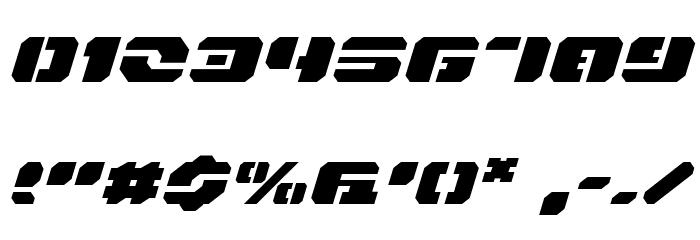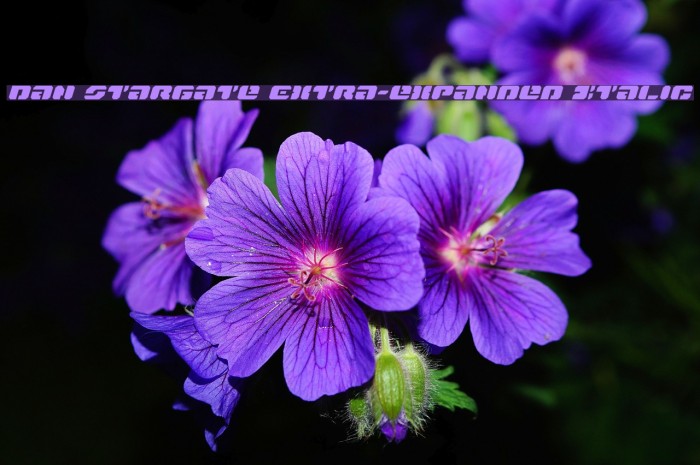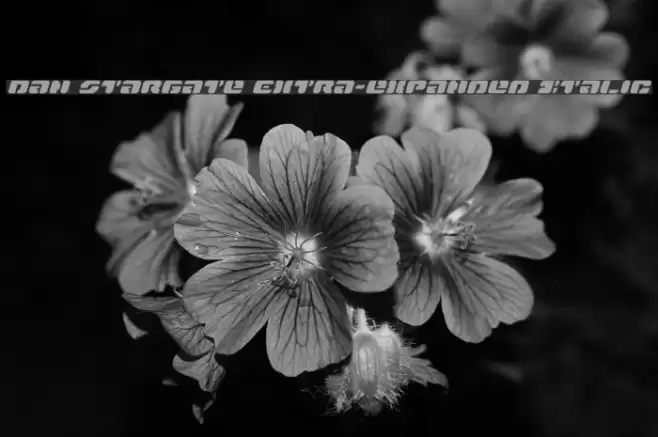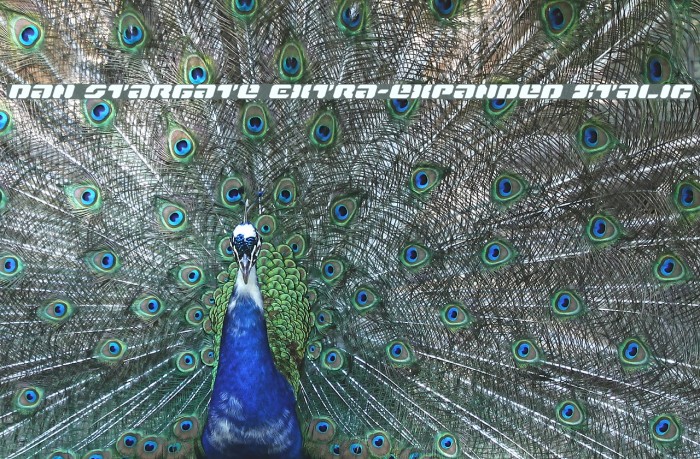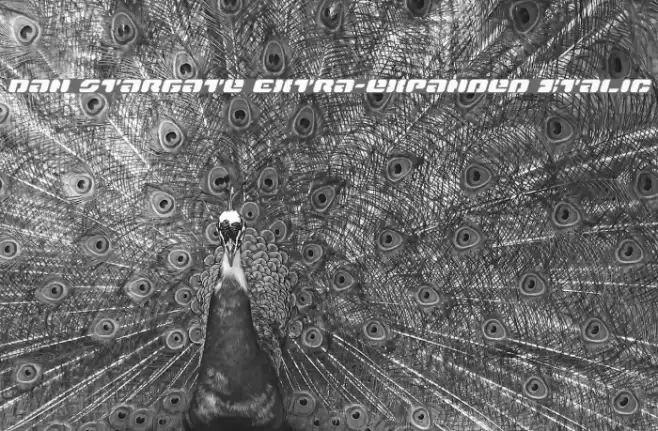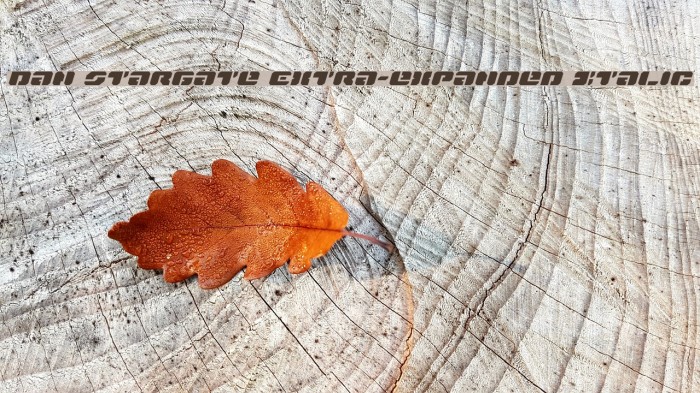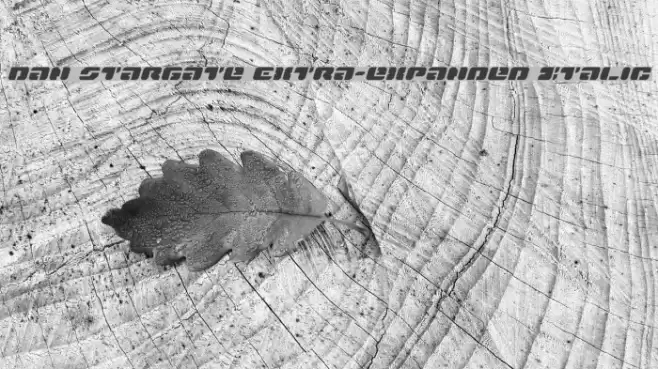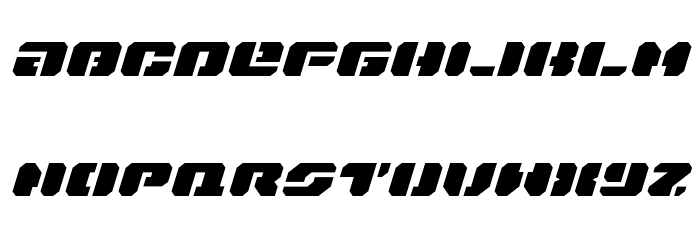
Dan Stargate Extra-expanded Italic Font
| Breite | Expanded |
| Gesamtstil | Futuristic |
| Vorgeschlagene Projekte | Ideal for sci-fi themed projects, video game titles, movie posters, and branding that requires a modern and bold statement. |